一、像对待图画像一样对待字体。
这是最难掌握的规律之一。字体也是一种图像,虽然看上去更像别的什么。此时更应考虑文字字体的视觉特性,与其他图像资料的关系,以及把它整合到整个构图中去。
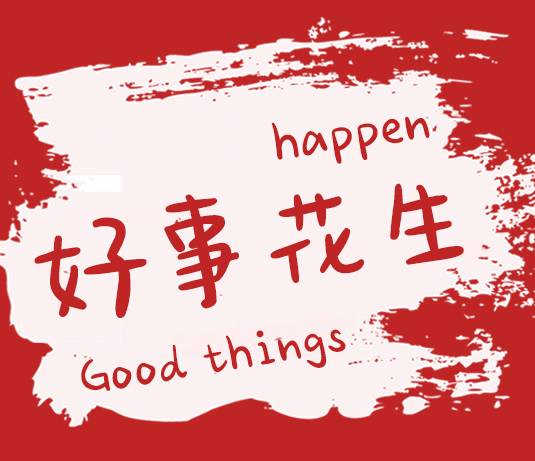
二、创造画像,不选现成素材。
随便找一些过时的照片,把它们按类型堆起来,这很容易。任何人都会做,很多人也是这样做的。但是至少应该把哪些找到的图像换成需要的图像,为客户,也为观众。